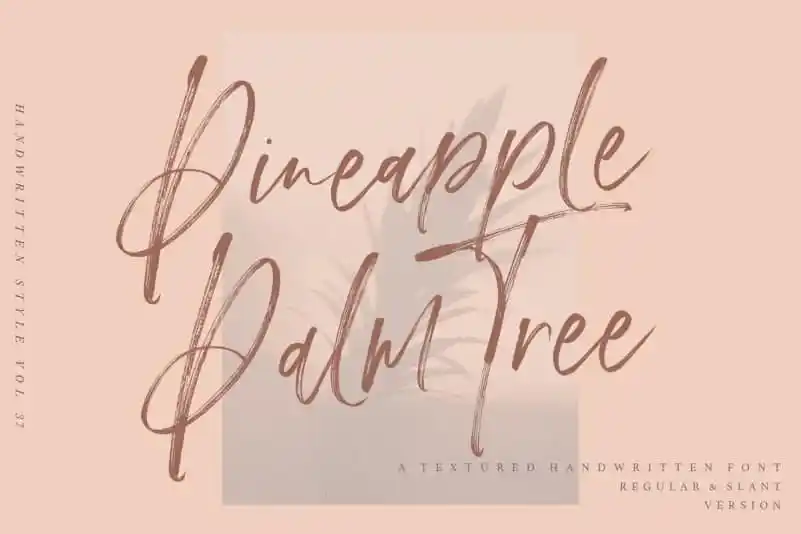
Pineapple Palm Brush Font – Download Grátis
A Pineapple Palm Brush Font é uma fonte escrita à mão que combina a essência do traçado de lápis com elementos naturais, tornando-a perfeita para quem busca um estilo elegante e único. Inspirada na árvore da canela, esta fonte oferece versões tanto ligadas quanto desenhadas em inclinação, permitindo aos designers experimentar diferentes estilos que vão desde um aspecto mais tradicional até uma escrita deslizante e forte. Ideal para trabalhos variados como a embalagem de convites, publicações nas redes sociais, logotipos, casamentos, marcações e design gráfico, esta fonte também pode ser usada em conjunto com várias tipografias serifadas. A Pineapple Palm Brush Font adiciona uma dose extra de personalidade às criações dos designers, tornando-a perfeita para quem busca uma maneira única de expressar a própria identidade visual. Seja você um profissional experiente ou iniciante na área do design gráfico, esta fonte é uma ótima escolha para tornar seus projetos ainda mais interessantes e distintivos.